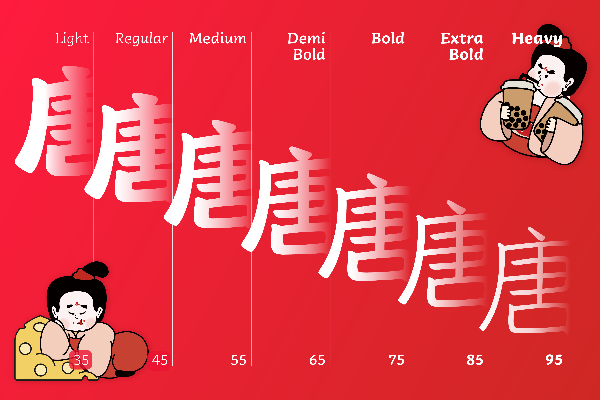
汉仪唐美人 35W
汉仪唐美人是汉仪字库倾力打造的一款充满盛唐风韵的艺术字体。汉仪唐美人字体结字方整,犹存隶书意韵,字型笔画胖胖可爱,整齐气息古朴而亲切。 汉仪唐美人字体如同从唐代仕女图中走出的美人,顾盼生姿,风情万种,旨在以其独特的艺术魅力,为现代设计带来一股浓郁的古典浪漫气息。它不仅仅是文字,更是对那个辉煌时代的一种致敬和再现。
李晓静
字体设计师,毕业于北京印刷学院。